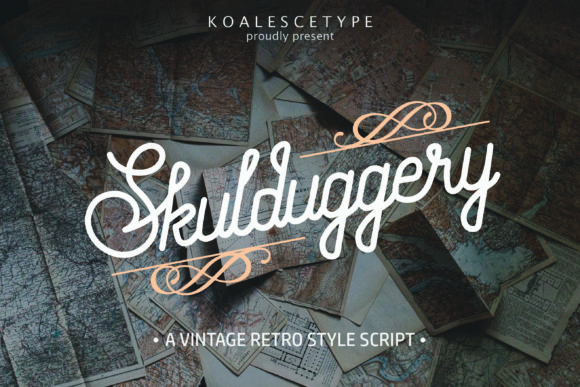
Creativefabrica Skulduggery Font
[Creativefabrica] Skulduggery Font
Skulduggery - это рукописный шрифт в стиле ретро, созданный для придания стильного штриха вашим заголовкам и логотипам проектов.
Этот шрифт читается как сильный, уверенный и динамичный и может добавить тонны ностальгического характера вашим дизайнерским работам.